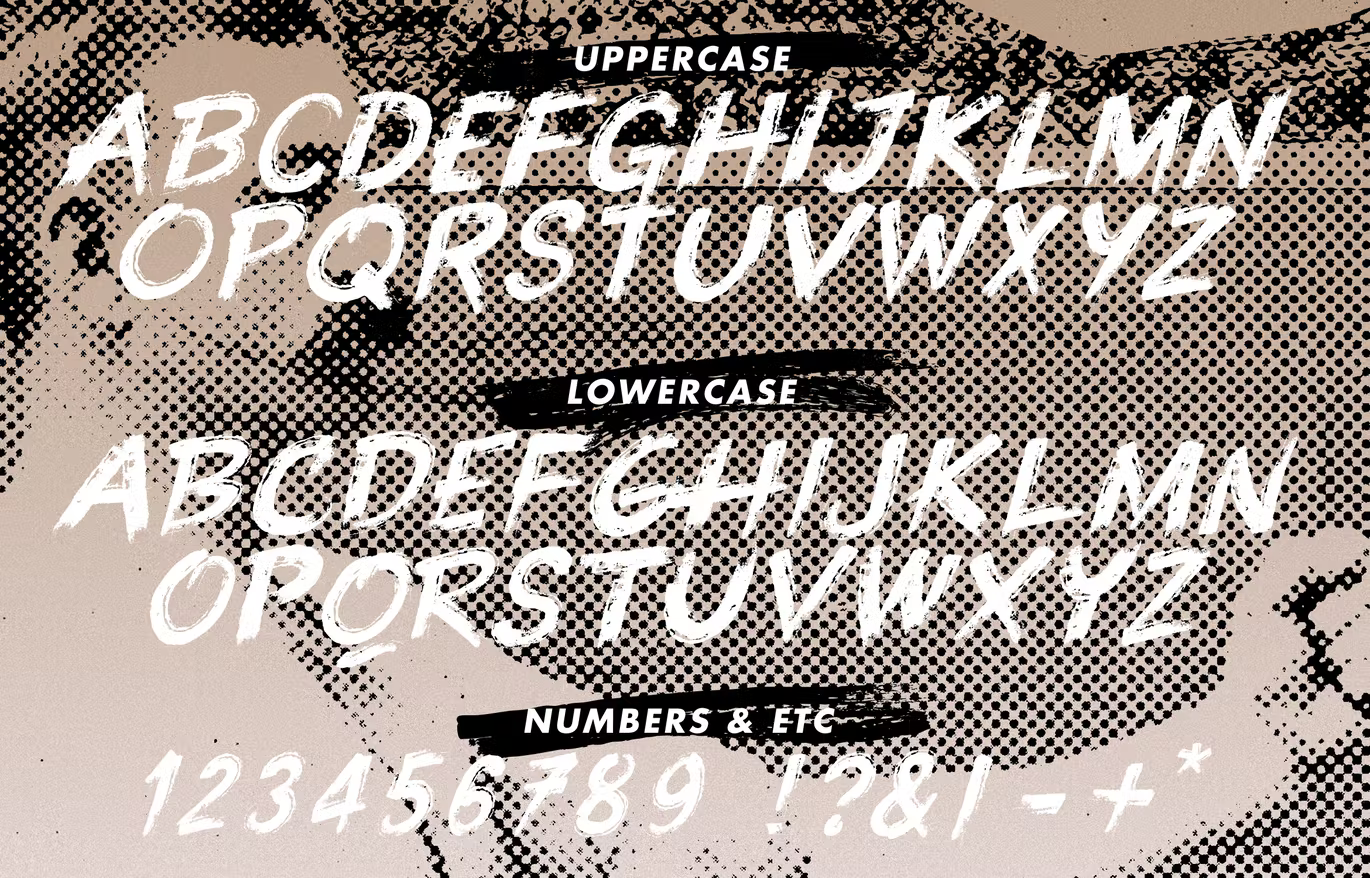
Knuckle Sandwich Font
Présentation Knuckle Sandwich. Une police de pinceau percutante avec plus de 300 glyphes. Utilise des majuscules et des minuscules pour les alternatives stylistiques, pour plus de facilité et de rapidité.
Des traits secs rapides et un style brut, Knuckle Sandwich est parfait pour les projets de marque, les impressions d’art avec un bord, les emballages de produits – ou comme superposition de texte avec attitude sur une jolie image d’arrière-plan.
Knuckle Sandwich prend en charge les caractères de base latins, d’Europe occidentale, d’Europe centrale et d’Europe du Sud-Est. Plus de 300 d’entre eux, faites-moi savoir par message s’il y a un personnage qui vous manque.